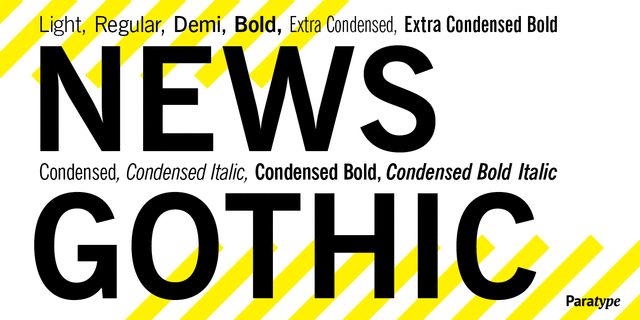
Версия фирмы Bitstream шрифта News Gothic, который был спроектирован Моррисом Бентоном и первоначально выпущен фирмой American Typefounders в 1908 году. Это стандартный американский гротеск первых двух третей двадцатого века, имеющий узкие пропорции и крупное очко строчных знаков. Несмотря на несколько необычные соотношения пропорций и форм, а может быть, благодаря им, News Gothic долгое время был очень популярен практически для любого применения. Кириллическая версия разработана для фирмы ParaType в 2005 году (дизайнер Дмитрий Кирсанов). Комплект знаков греческого алфавита спроектирован Дмитрием Кирсановым в 2009 году
Ассоциации c семейством News GothicКачества и характер:
деликатный, чистый, легкий, прохладный, свежий, городской, деловой, серьезный, стабильный, статичный, устойчивый, офисный, строгий, глобализированный, глобалистичный, простой, ровный, качественный, стандартный, безразличный, равнодушный, официальный, точный, убедительный, прямоугольный, твердый, надежный, уверенный, сильный, индустриальный, техногенный, мотивирующий, ответственный, инженерный, чертежный, авторитетный, урбанистический, современный, монотонный, логичный, прагматичный, практичный, искусственный, холодный, машинный, урбанистичный, умный, высокий, крутой, железнодорожный, громкий, важный, амбициозный, военный, тяжелый, железный, архитектурный, рабочий
город, офис, бизнес, дизайн, коворкинг, политика, промышленность, техника, станок, инструмент, прибор, электростанция, энергетика, завод, наука, технологии, инженер, лекарство, медицина, аптека, новости, архитектура, небоскреб, урбанистика, автоматика, институт, конструктор, стройка, строительство, чертеж, железная дорога, космос, армия, оружие, машиностроение, порт, авиация, самолет, вагон, тренажеры, ремонт, ракета, спутник, страйкбол, архитектор, футбол, рабочий Стилистика: